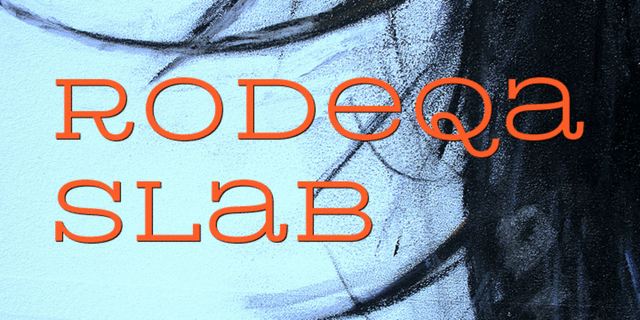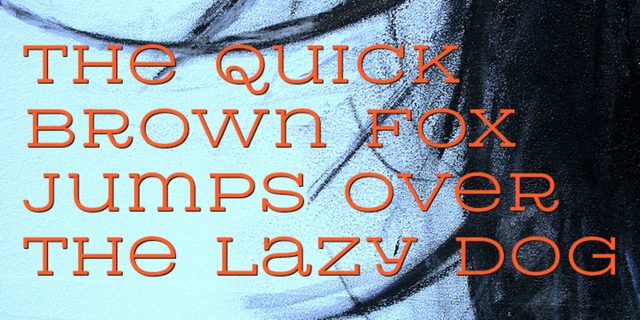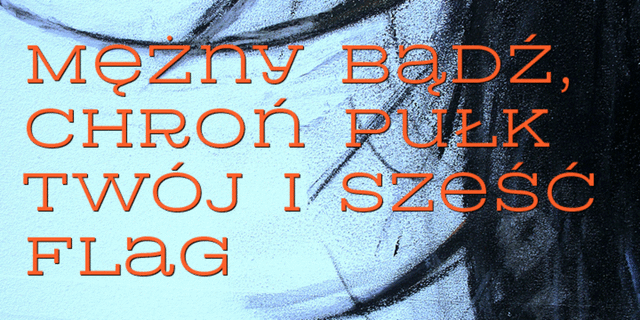
Шрифт в стиле ковбойских родео для заголовков и плакатов. Разработан Сергеем Ткаченко в 2011 году.
хипстерский, традиционный, устойчивый, качественный, добротный, четкий, самостоятельный, западный, статичный, ровный, твердый, деревянный, просторный, ремесленный, крафтовый, громкий, убедительный, броский, заметный, серьезный, ковбойский, мотивирующий, мачо, амбициозный, бандитский, винтажный, кинематографичный, внушительный, тяжелый, авторитетный